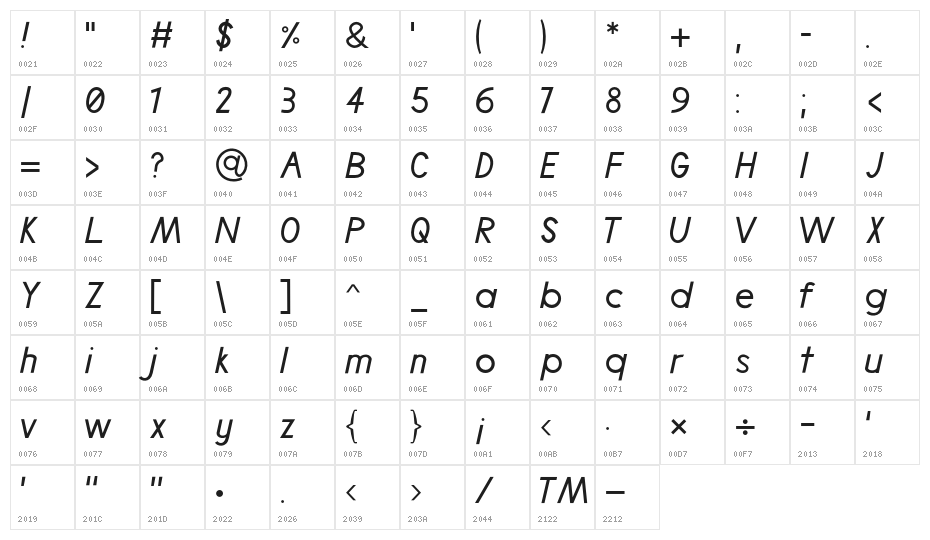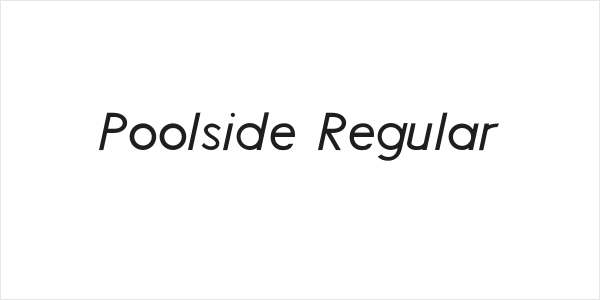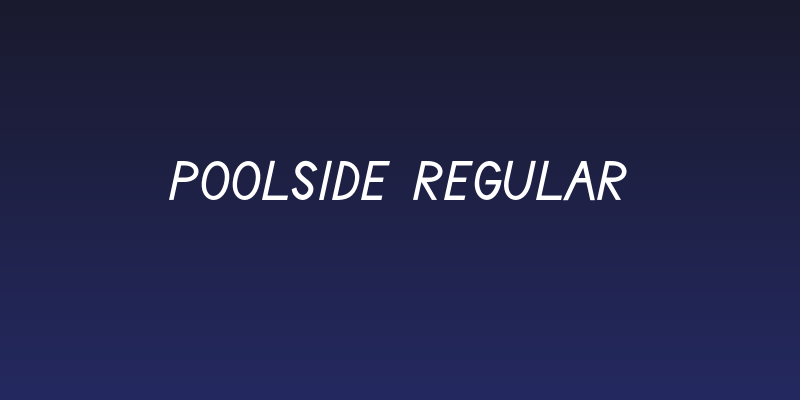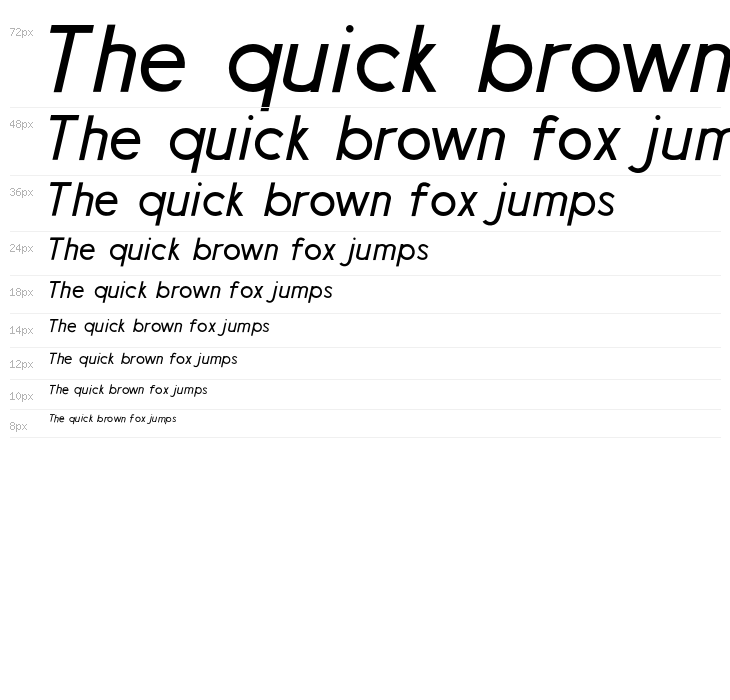
Poolside Regular Font
✎ Sans Serif
| Anwendungsfall | Headlines, Body text, Logos |
| Vorgeschlagene Projekte | Ideal for branding, advertising, web design, and editorial projects that require a modern and professional appearance. |